20 superbes polices de conception de logo dont tout grand designer a besoin
La conception d'un logo peut vous causer beaucoup de problèmes, surtout si vous voulez qu'il ait l'air bien équilibré et complet. L'un des éléments les plus importants de presque tous les logos est la typographie qui exprime des informations précises sur l'entreprise que les clients doivent connaître. Par conséquent, la typographie mérite beaucoup d'attention lors de la réflexion sur le futur logo.
Indéniablement, en tant qu'identité visuelle d'une marque, avoir un logo bien conçu est la principale exigence pour chaque entreprise. Il se compose de couleurs, de formes, de polices et de nombreux autres éléments de conception pour le rendre séduisant. L'utilisation appropriée de ces éléments donne à votre marque une identité créative et unique qui vous démarque de la concurrence.
Parmi ces nombreux éléments de conception, une chose qui inquiète toujours les concepteurs est de sélectionner les polices pour la conception du logo de l'entreprise. Il existe des milliers de polices de caractères disponibles sur Internet, et parmi ces polices qui donnent un look attrayant, il est difficile de décider.
Quelles filiations apporteront-ils au style abstrait ? Quelles spéculations vont-ils faire sur votre personnage d'image qui y est soumis ? Pour répondre à ces sollicitations et ce n'est qu'une trace de quelque chose de plus grand, nous avons rassemblé ces conseils et règles pour vous aider à choisir un style de contenu de logo personnalisé qui vous convient clairement. Enquêtez sur pour découvrir les polices de caractères qui conviennent le mieux à votre image.
Étant le facteur le plus important de toute la conception d'un logo personnalisé, une seule erreur dans sa sélection peut casser votre conception. Ainsi, vous devez identifier une ou deux meilleures polices qui ont l'air parfaites dans la conception de votre logo et qui maintiennent le professionnalisme de la marque. Alors, discutons de certaines des meilleures polices que vous pouvez utiliser dans votre logo et rendez-le attrayant.
1. Abel
Aabel appartient à la catégorie des polices serif. Cette police moderne est esthétique dans la conception de votre logo et convient particulièrement aux marques de luxe et de mode.
En fait, il est livré avec les trois poids : normal, gras et léger. Toutes ces versions sont magnifiques dans les lettres majuscules et minuscules. Non seulement dans la conception de logo d'entreprise, cette police convient aux affiches, en-têtes, publicités, conception d'emballages, livres et bien d'autres endroits. Toute combinaison de polices avec celle-ci a fière allure dans votre logo, par conséquent, ce ne sera pas un mauvais choix de l'utiliser.
2. Garamond
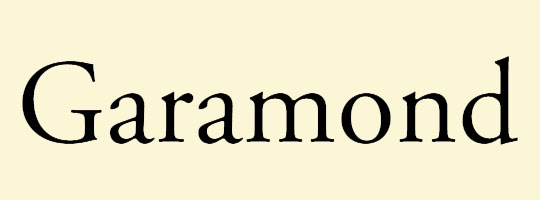
Garamond est l'une des plus anciennes polices de caractères à empattement datant du XVIe siècle. Tirez le meilleur parti de cette police en ajoutant votre logo personnalisé, cela donne un look élégant. Présentez la personnalité et le professionnalisme de votre marque avec cette police de caractères en l'utilisant dans un logo.
Il s'inspire à l'origine des coupes à l'emporte-pièce de Claude Garamond ; actuellement, vous pouvez obtenir de nombreuses variantes de cette police particulière. Le plus populaire est Adobe Garamond qui est conçu par Robert Slimbach. En raison de sa lisibilité, il est également utilisé dans les magazines et les journaux.
3. Rockwell
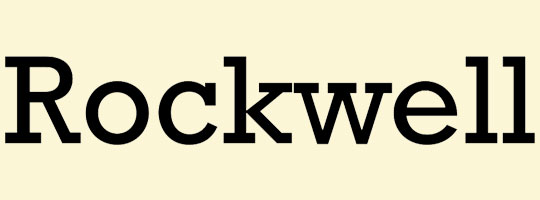
Une autre meilleure police de logo qui rend votre design encore plus accrocheur. Il appartient à la famille de polices slab serif. Bien qu'il ait été conçu en 1934, il est actuellement sous les feux de la rampe et peut être utilisé dans la conception du logo de l'entreprise.
Il a été utilisé dans la signalisation informative à l'Expo 86, le train léger Docklands a utilisé le poids audacieux du Rockwell dans les années 1980. En raison de sa course mono-pondérée, il est principalement utilisé dans la petite taille.
4. Frutiger